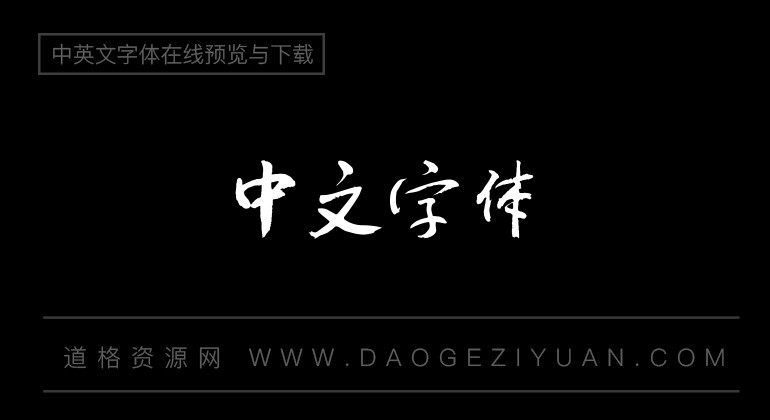
逐浪报人书法行体
逐浪报人书法行体是一种汉字书法体,由中国知名书法家及报人编辑部长汪景华先生设计,以“报人”为主题,由报人编辑部长汪景华先生设计而成,结合书法精髓,把报人的职业特点、精神、文化以及报人精神融入其中,形成一种报人专属的书法体。这种书法体具有报人的精神,有报人的气质,它的书法行体也有着独特的美感,它的笔画比一般的书法体要宽,笔划要更加流畅,它的笔画比较淡,比较柔和,它的书法行体也有着独特的美感。
逐浪报人书法行体是一款非常不错的手写艺术字体,具有很好的视觉感,适合于文化类的宣传设计、商业类品牌的广告和产品包装设计以及个性化文字排版等较多场景。
逐浪报人书法行体字符映射图